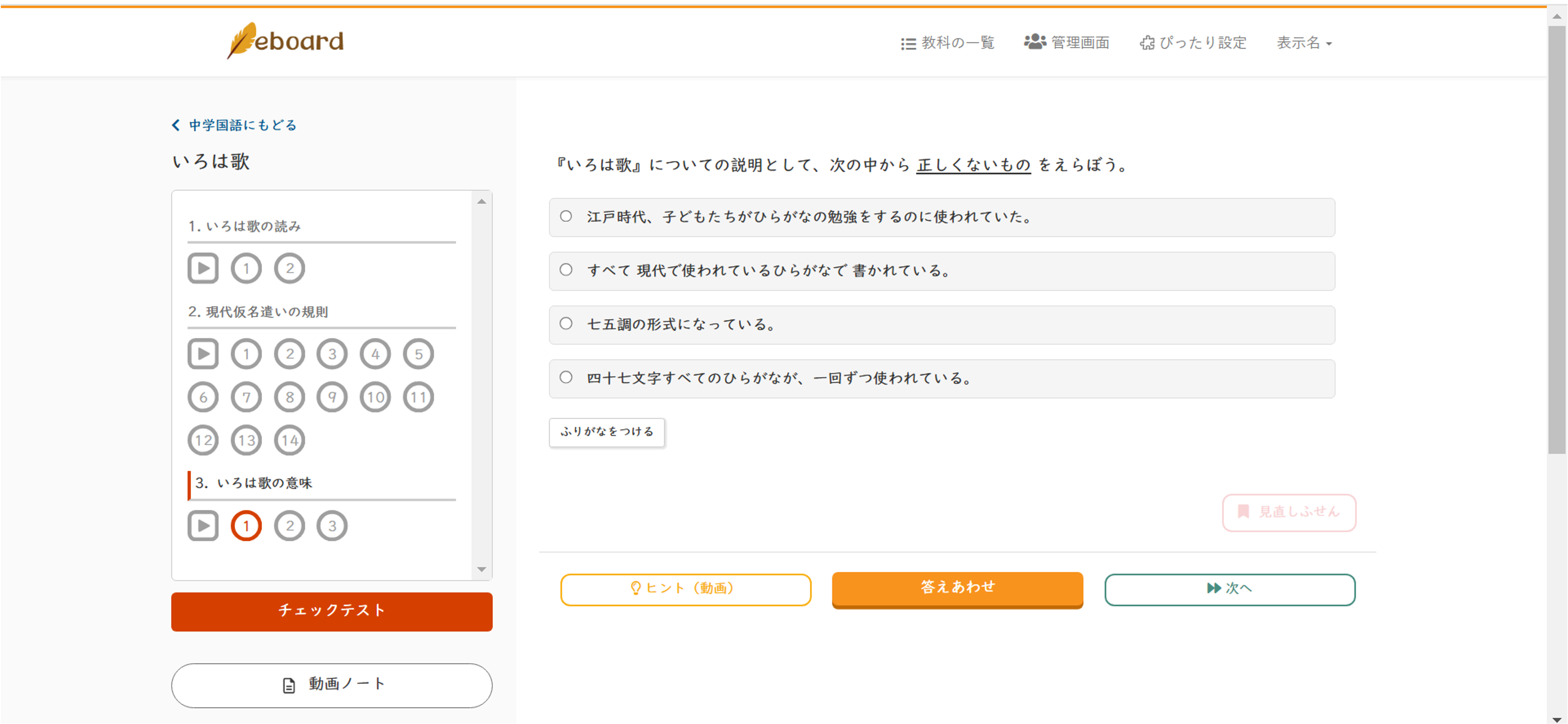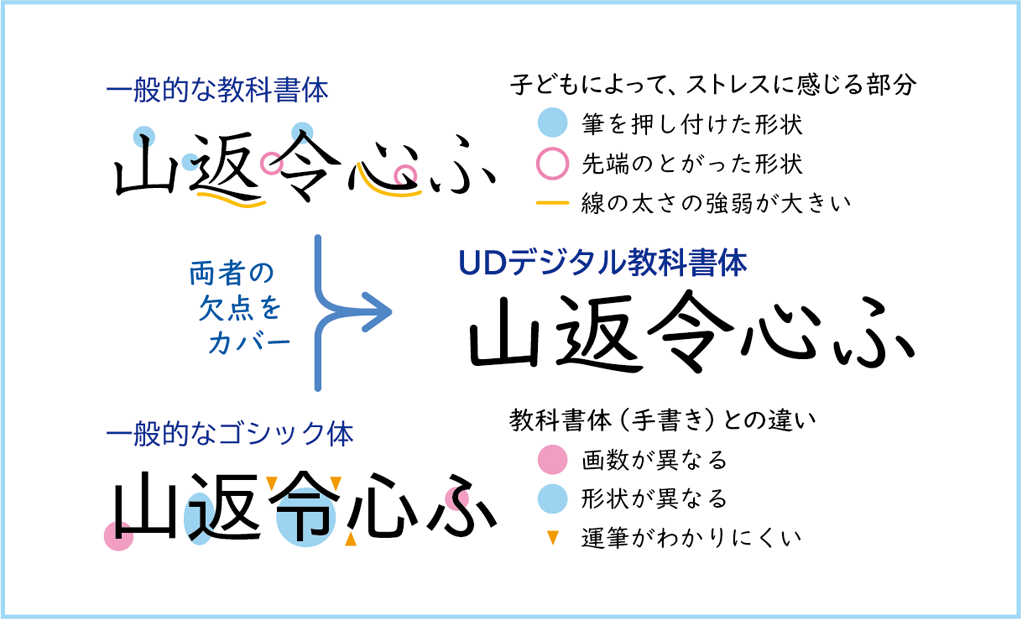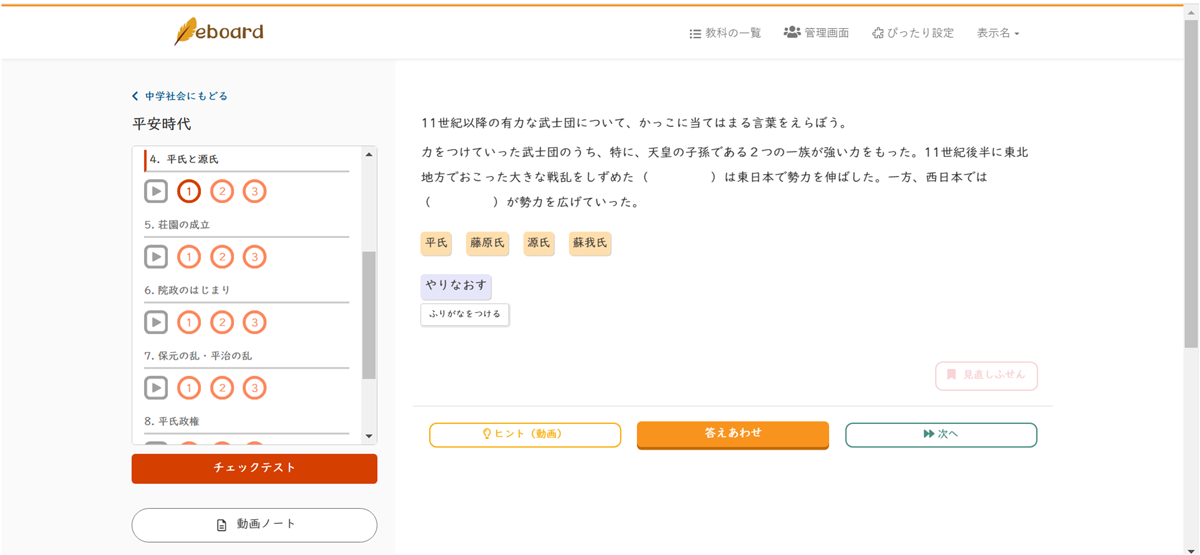
「学びをあきらめない社会」の
実現を目指して
ICT教材eboardの開発・運営
NPO法人eboard(以下、eboard)は「学びをあきらめない社会」というミッションの実現に向けて活動する団体です。塾に通えない、授業についていけない、学校に行けないなど、さまざまな理由から「学びをあきらめてしまっている」子どもたちがいます。たとえ、どんな環境にあっても、子どもたちが「学んでみよう」と思ったとき、子どもたちの学びを「支えたい」と思ったとき、「いつでも、どこでも」それが実現できる。そんな「学びをあきらめない社会」の実現を目指して活動しています。
2023年には、「第2回 SDGsジャパンスカラシップ岩佐賞(SDGs岩佐賞)」(主催:公益財団法人岩佐教育文化財団)を受賞。その活動が社会的に高く評価されるなか、代表理事の中村孝一氏に、毎月の利用者が20万人を超えるICT教材eboardに「UDデジタル教科書体」(TypeSquare)を採用したお話をお伺いしました。
私たちは「学びをあきらめない社会」をミッションに掲げて活動しているNPOです。教育分野のNPOというと、学校・教育現場での活動をされている団体が多いですが、私たちは、2013年の設立時から10年以上に渡って、インターネットを通じて、経済的理由や不登校、障害などの事情で学びにアクセスしづらい、つまずきを抱えている子どもたちに、学習機会を提供しています。
具体的には、約2,000本の映像授業と約10,000問のデジタルドリルで構成されたICT教材eboardを開発・運営しています。この教材は全国の公立学校や学習支援団体、フリースクール、地方の公営塾など全国10,000カ所以上の教育現場で導入されていて、毎月20~30万人の方々に利用されています。
ICT教材eboardは、公立学校・非営利活動、ご家庭での利用には無料で提供しています。以前はご家庭での利用も多かったですが、1人1台の端末が整備された2021年以降は、全国の公立学校で、普段の授業の中で使ってもらうということが一番多いです。
コロナ禍の影響も大きくあり、文部科学省や全国の教育委員会から学校にご紹介いただき、全国一斉休校になった2020年の3〜5月には、100万人以上の方に学びを届けることができました。
ただ、コロナ禍以降、利用者が広がる中で、私たちは改めて、障害や言語、さまざまな障壁から学びにアクセスできない子どもたちの存在を大きな課題として認識することになりました。2022および2023年度の個人アカウント申請理由(複数回答)の中では、「障害や特性等から、学習に困難がある」と回答した人が4割近くいたのです。
学習障害をはじめとした発達障害を抱えている子や、診断はなくても、発達の遅れや特性の凸凹から、通常の授業や紙での学習だと学びづらい子が多いです。中でも割合として多いのが、読み書きに困難を抱えるディスレクシアの子どもたちです。日本では、ディスレクシアに関する調査が十分に行われてはいないのですが、全人口の5〜10%がディスレクシアとも言われています。そのまま計算すれば、35人のクラスに2〜3人程度はいる計算になります。
学校生活や学習面では、教科書の音読が難しい、板書が追いつかない、などの困難を感じることが多いようです。また、それにより周囲にやる気がないと誤解されたりする、本人の意欲の低下が起きるなどの深刻な二次障害が起こりがちなところも大きな問題です。
学校・団体利用アカウントでの「UDデジタル教科書体」導入
UDフォントの存在は以前から見聞きしていて、学校・教育現場の先生から、UDフォントを選べるようにしてほしい、という声をもらうこともありました。そんな中で、2023年にモリサワの方からUDフォント開発の経緯やお話を伺ったのですが、私たちにとって決め手になったのは、「UDデジタル教科書体」がディスレクシア、ロービジョン(弱視)などに配慮しているところです。
読みに困難を抱える子は、一般的な教科書体や明朝体の形状や線の強弱などにストレスを感じたり、手書きの文字との違いに戸惑ったりすることがあります。「UDデジタル教科書体」は、そうしたフォントの欠点をカバーし、書き方の方向や点・ハライの形状を保ちながらも、太さの強弱を抑え、読みやすさを重視したフォントになっています。書体の選択肢を増やすことにより、学習に取り組みやすくなる子どもたちがひとりでも増えることを願って、学校・団体としての利用アカウント向けに導入しました。
導入後、現場の先生からは「導入してくれて本当にありがたい」という声とともに、「選択できることがいい」というのをよく聞きます。フォントに限ったことではないですが、子どもたちにとって選択肢があること、先生方がそれを子どもたちに提示できることがやはり大切なんだなと感じました。
最近のニュースとしては、デジタル庁が運営するオウンドメディア「デジタル庁ニュース」の動画内で、子どもたちがICT教材eboardを使用する様子が紹介されました。
鹿児島市にある鹿児島市立八幡小学校の様子が紹介され、「自由進度学習」と呼ばれる授業の中で子どもたちがICT教材eboardを使用しています。
「自由進度学習」は、子どもたちが一人一台のタブレット端末を使い、教科書に加えて複数のICT教材から自分に合ったデジタルドリルを選択し、それぞれのペースに合わせて「自分らしく学習」しています。
UDフォントの存在も大事なのですが、それが開発され世に出たことで、「フォントによって、読みやすさが変わる」「読みやすくなる子がいる」という事実が広まったことは、本当に大きなことだと思っています。モリサワさんでは、「見やすさ」「読みやすさ」の実現のために、フォントの話だけにとどまらず、フォントの選び方、文字サイズの設定、文章の行間やスペースの取り方など、「伝わる」制作物の作成方法を広める活動もされています。フォントによって読みやすくなる子もいれば、そうでない子もいる。紙の材質や印刷の仕方などで、読みやすさが変わる子もいます。
今後も、フォントにとどまらず、子どもたちが感じる読みづらさや学びづらさ、そしてその解消に向けた取り組みを、どんどん進めていってもらいたいです。それは、私たちのミッションである「学びをあきらめない社会」につながるもの。一緒にそんな取り組みができると嬉しいですね。